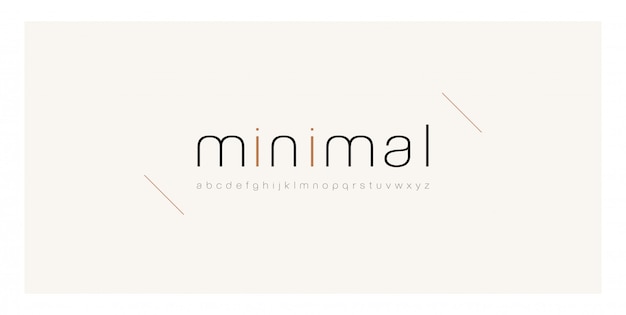
Minimalne Nowoczesne Czcionki I Cyfry Alfabetu Streszczenie Miejskich Cienka Linia Czcionki Typografii Krój Czcionki Wielkie Litery Małe Litery Ilustracji Wektorowych